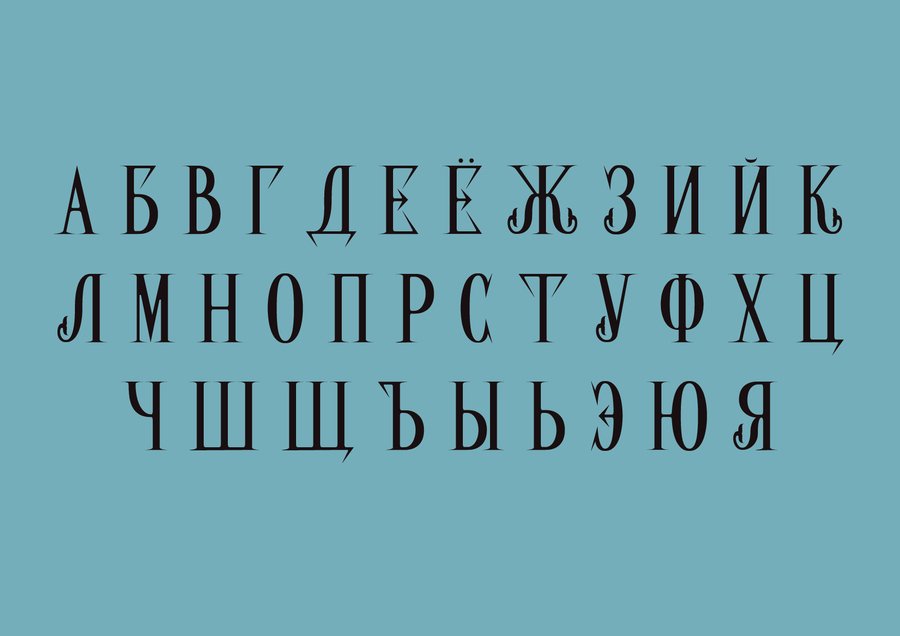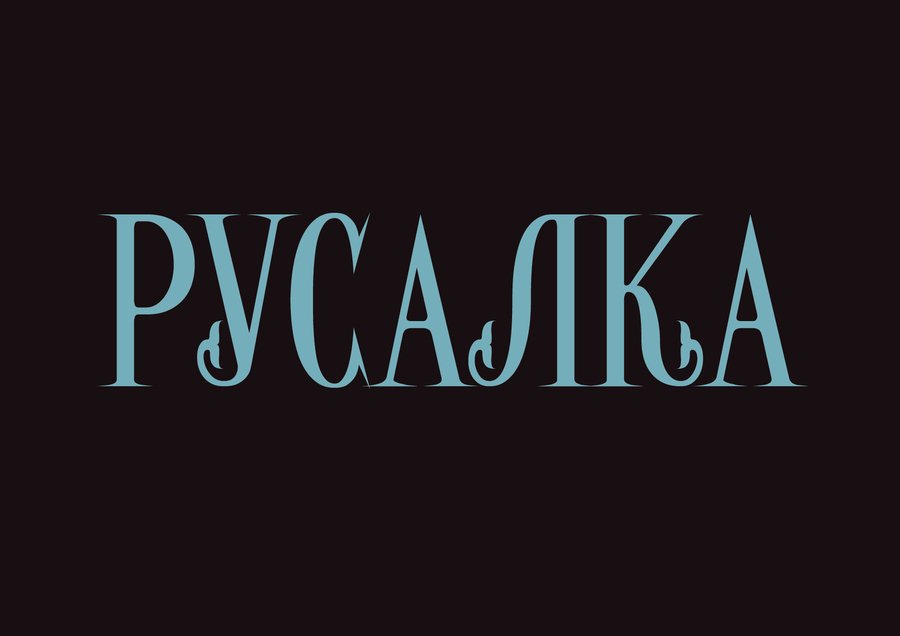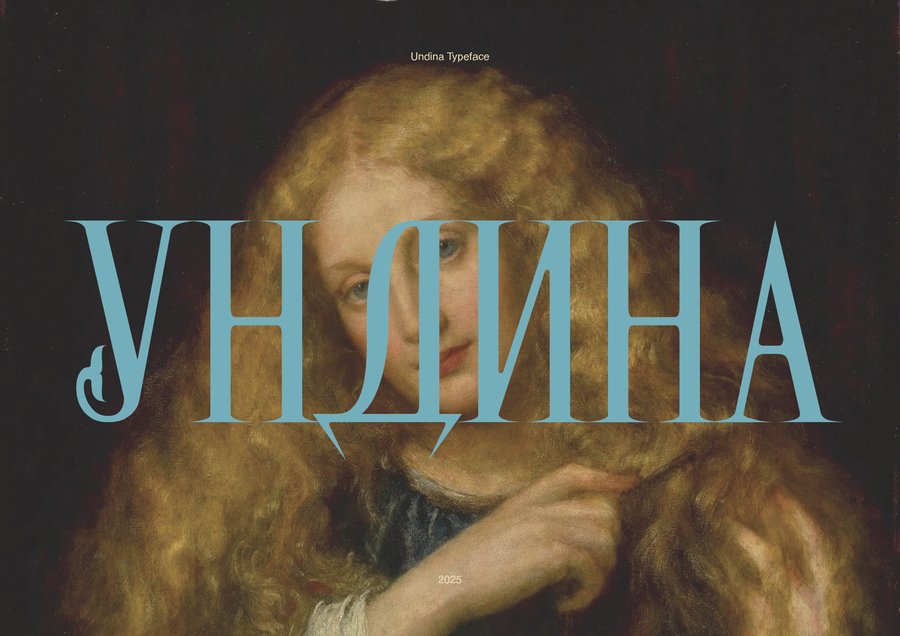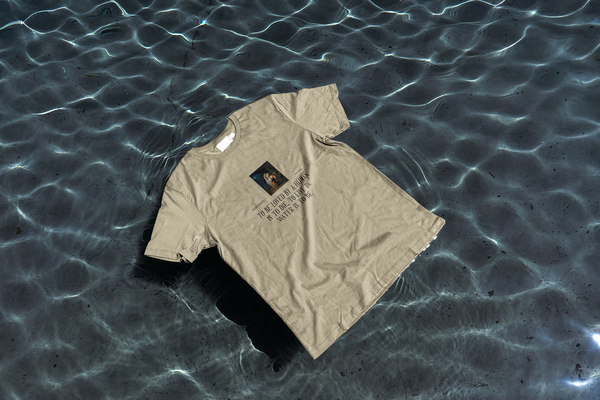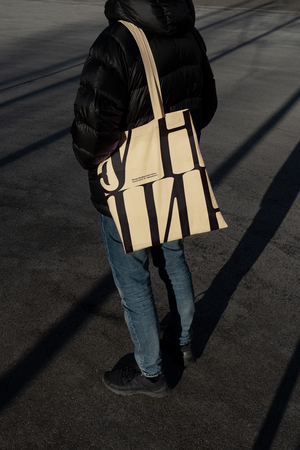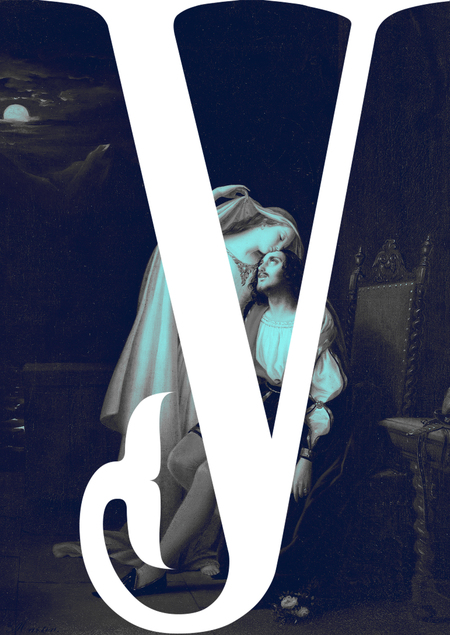
Undina Typeface — шрифт, созданный на основе немецкой сказки Фридриха де Ла Мотт-Фуке и оперы П. И. Чайковского «Ундина». Он соединяет в себе трагичный образ отвергнутой русалки-нимфы и строгость и остроту рыцаря.